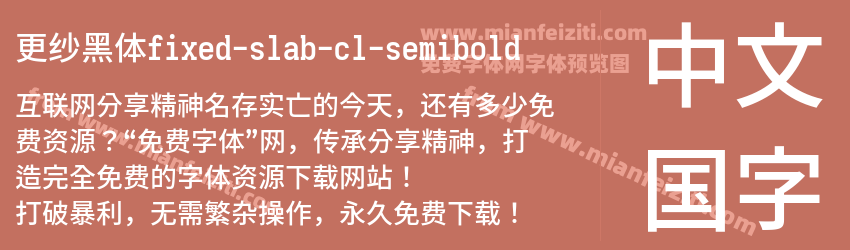
更纱黑体fixed-slab-cl-semibold
字体名称: 更纱黑体fixed-slab-cl-semibold
Postscript名称: Sarasa-Fixed-Slab-CL-Semibold
本款“更纱黑体fixed-slab-cl-semibold”是一款书写很新颖的字体,字体大方,适合各种设计作品使用!欢迎下载!